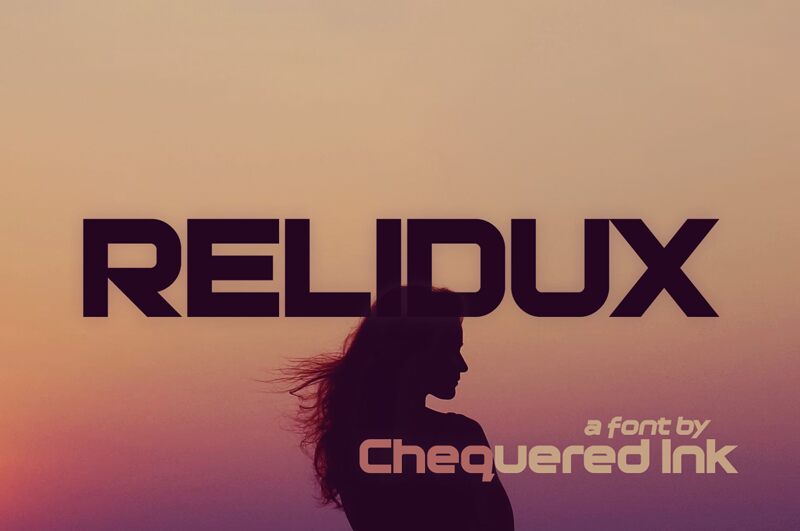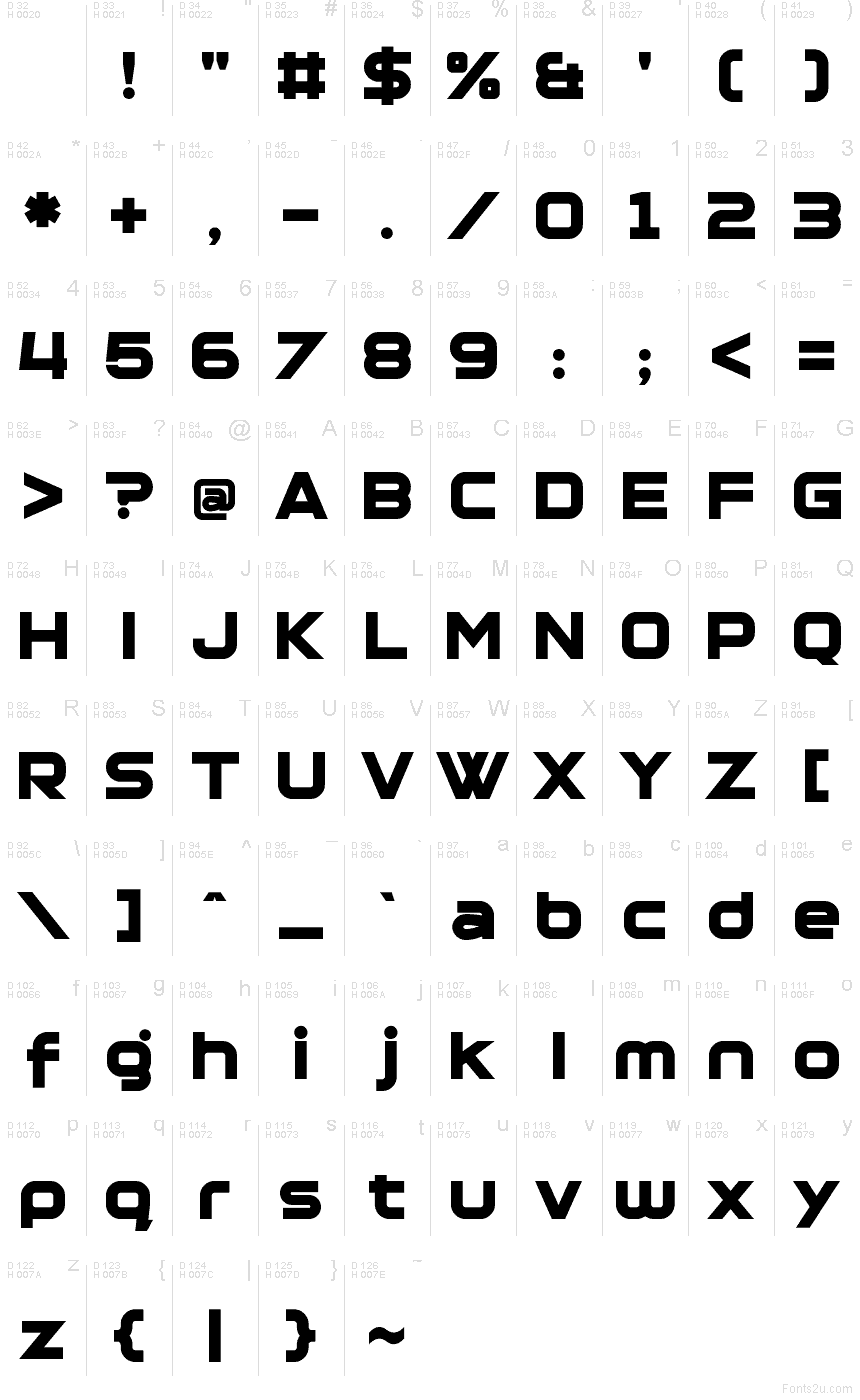
Relidux, une police display géométrique moderne signée Chequered Ink, allie lettres imposantes, courbes amples et jonctions aux coupes franches. Ses formes arrondies évoquent la robustesse et le futurisme, tandis que des découpes diagonales décisives empêchent cette structure lisse de paraître trop douce ou fantaisiste.
Cette police gratuite est idéale pour l'identité visuelle de marques technologiques, les logos de jeux vidéo, les visuels musicaux, les affiches d'événements, le packaging et les titres éditoriaux. Elle se distingue particulièrement dans des mises en page courtes et surdimensionnées, où ses formes denses et ses détails tranchants peuvent s'exprimer pleinement sans fioritures superflues.